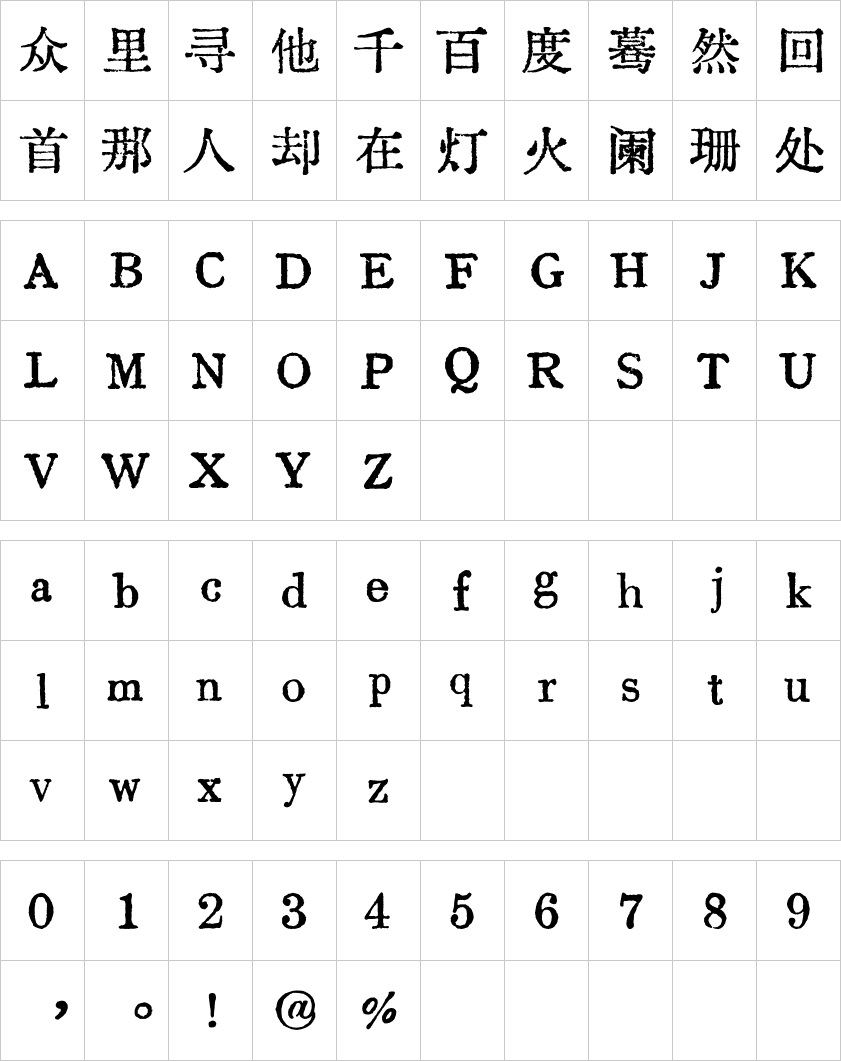
汇文明朝体
本字体制作始于2019年1月份,因一切开始于是我扫描《文汇报》上面的《汉字简化方案草案》,后来又收集、扫描了各种历史文献资料,汇总挑选而形成了这样一款字体,故名「汇文明朝体」。
本字体的字形来源主体为五六十年代官方各种汉字改革文件,简体字部分基本复原汉字简化后、字形改造前的书籍印刷体样貌。繁体字、传承字部分基本还原民国至共和国初期字形样貌,是比较原滋原味的旧铅字印刷风格。
本字体平片假名及一些符号来源于Oradano明朝,其实要说起来,本字体的史祖就是Oradano明朝。
因为最开始做的时候,我对于字体的字距、大小什么的,完全不会调,也不知道要怎么设置各种数据,所以就直接取了「Oradano明朝」这个字体作为壳子,把里面的东西一一替换成我的字形,慢慢地替换到最后,才形成了汇文明朝体。就是说,其实这是一艘忒修斯之船。